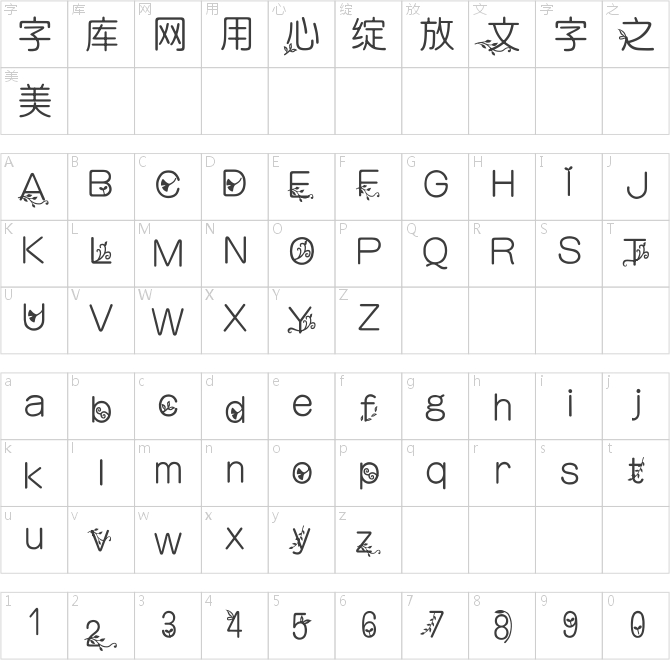
字體名稱: 夜夜相思體
夜夜相思體
夜夜相思體字體羿創(chuàng)夜夜相思字庫(kù)是一款讓人賞心悅目、百看不厭的中文字體,適合各類廣告和產(chǎn)品包裝設(shè)計(jì)應(yīng)用,字體大小2.59MB,格式為ttf字體,上傳用戶是浪遍塞納河的,作者/版權(quán)方為羿創(chuàng)字庫(kù)